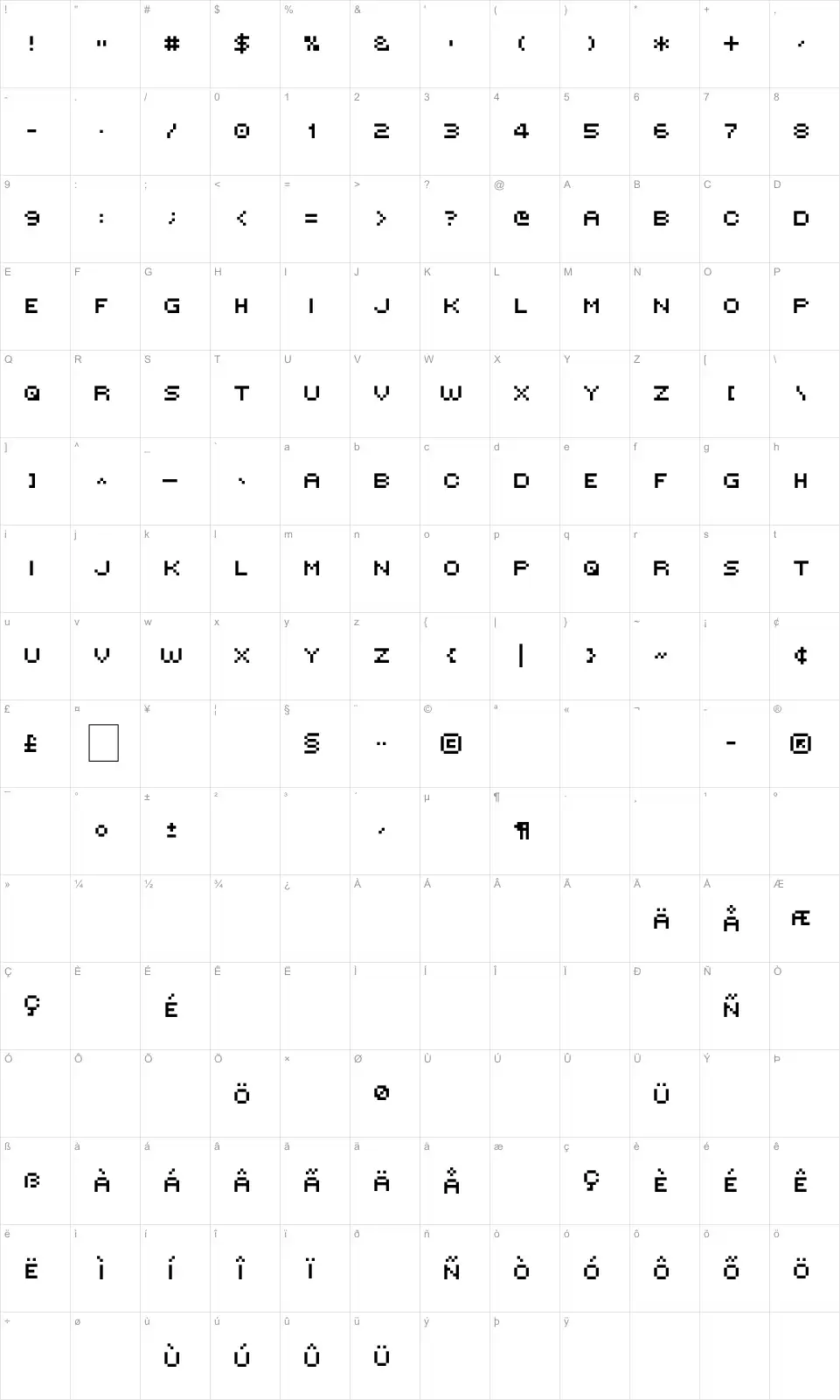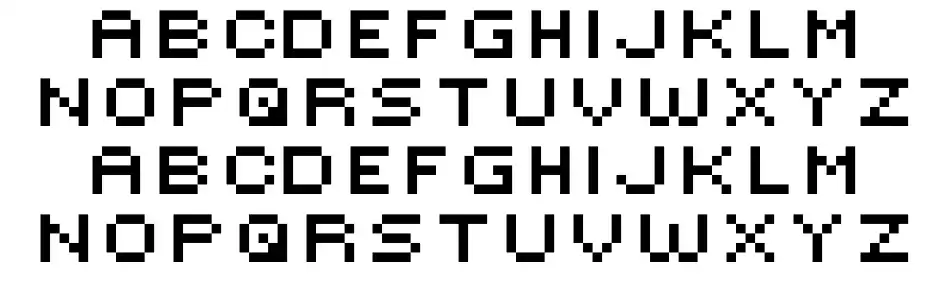
Descubra a Victor’s Pixel Font, criada pelo designer talentoso Sergeant Koopa. Esta fonte techno pixelada oferece uma experiência única e vibrante para seu próximo projeto. Se você está procurando por essa fonte, agora é o momento de baixá-la ou gerar um preview personalizado online para ver como ela se assemelha antes de aplicá-la. A Victor’s Pixel Font, que pertence à categoria Pixel, é licenciada sob uma permissão gratuita e está disponível em formato TTF. Adicionada à nossa biblioteca em 12 de julho de 2022, a Victor’s Pixel Font já foi baixada mais de 1.996 vezes. Com um tamanho de apenas 9 KB, essa fonte é extremamente leve e leve, permitindo que você a use em todos os seus projetos de tecnologia e pixel art com facilidade. Para mais informações, visite o website do designer: https://bigdaemon.net.